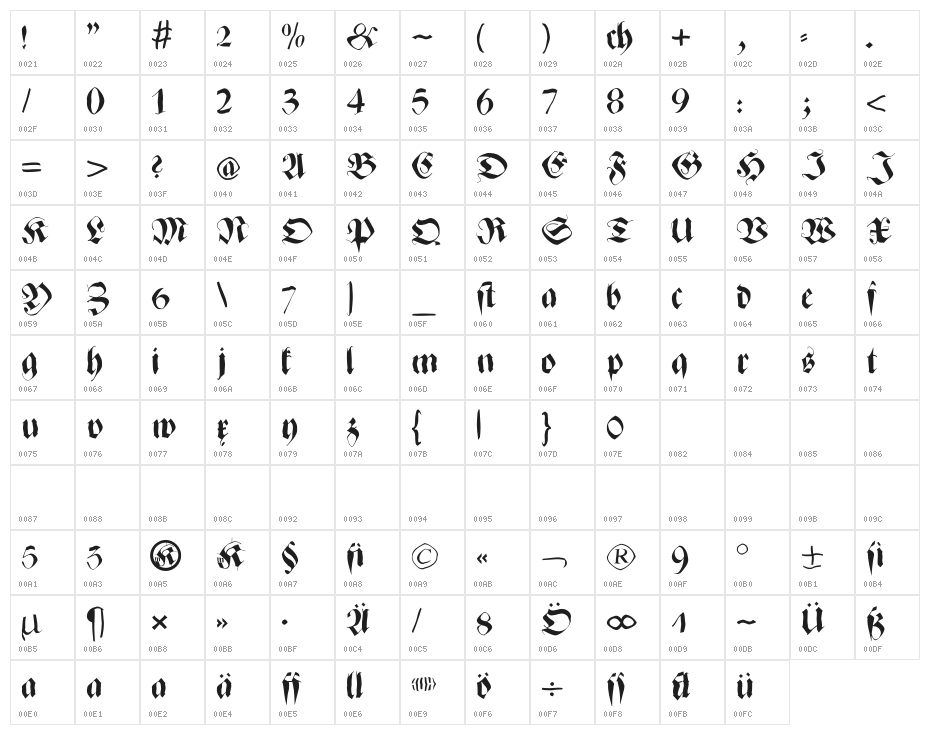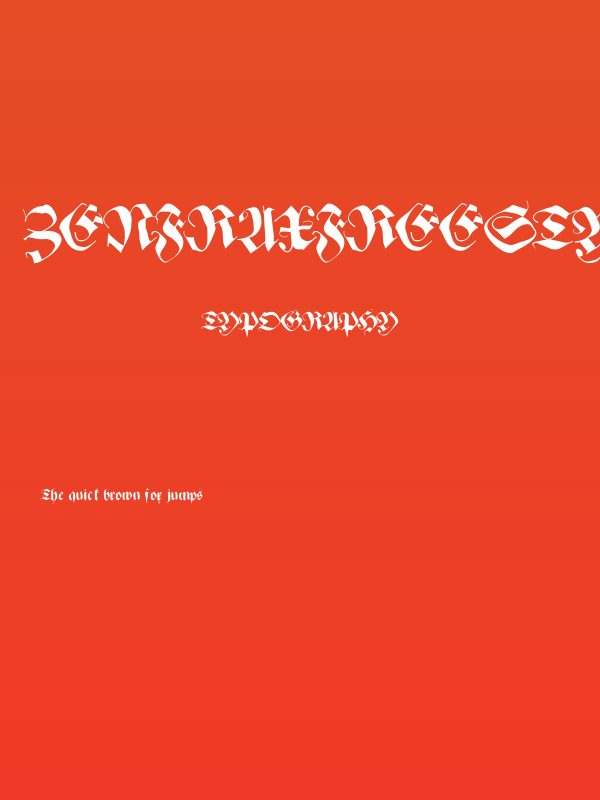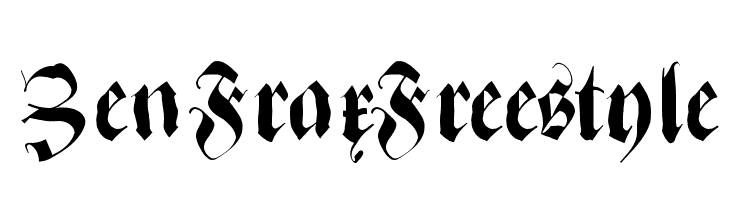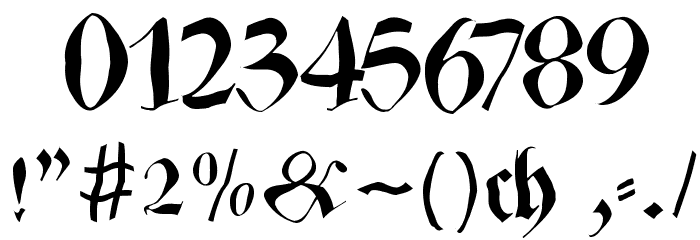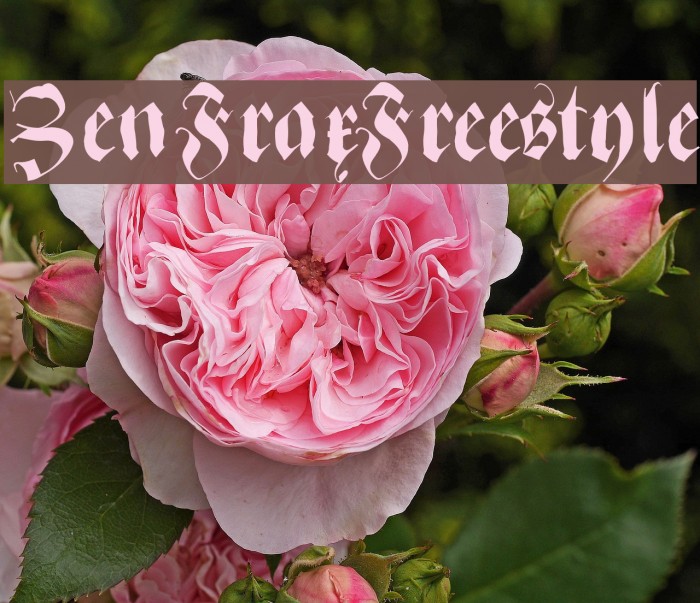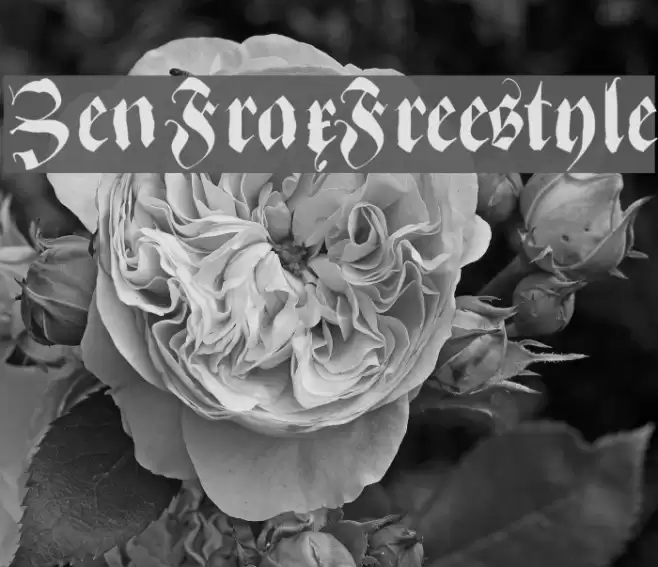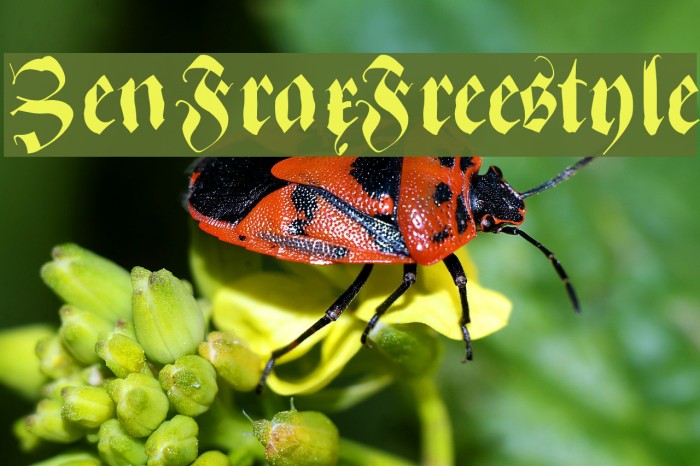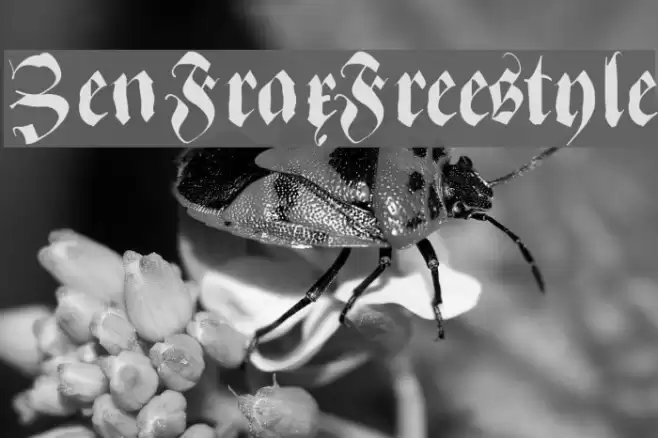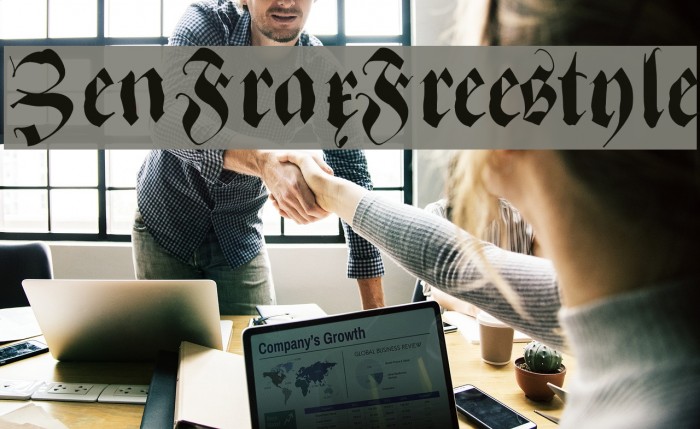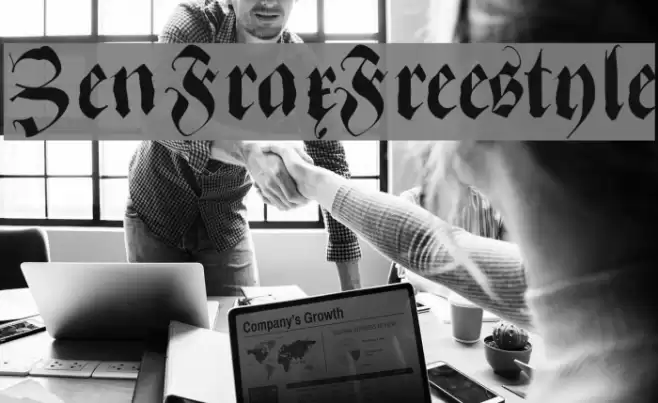
ZenFraxFreestyle Font
| الفئات | Gothic |
| النمط العام | Vintage |
| حالة الاستخدام | Logos, Headlines, Decorative purposes |
| مشاريع مقترحة | Suitable for historical documents, gothic-themed designs, book covers, or event invitations that require a traditional or dramatic flair. |